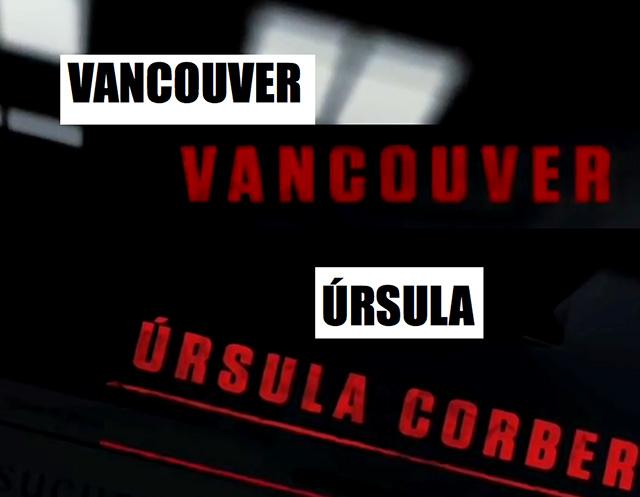
Schriftart Haus des Geldes (Netflix-Serie)
Liebe ForumsleserInnen, welche Schriftart wird im Vorspann von "Haus des Geldes" verwendet? Hier der Link zum Youtube-Video:
Das sieht auf den ersten Blick wie eine Impact mit Stempeleffekten aus ...
Edit: Auf den zweiten Blick leider nicht mehr ganz so ...
Hier sieht man es noch mal deutlicher:
Noch mal Edit: Dann wird's vielleicht die Compacta sein ...
Sieht mir nicht so aus … die Compacta ist schmäler und deren C offener.
Miſt! Dann wäre die Tungsten gemäß whatfontis ein guter Kandidat.
Und dann war da doch noch was?  Nö, hab mich getäuscht. Es gibt einiges von diesen Schriften ...
Einfach mal durchwühlen. Allerdings habe ich einige in diese Rubrik fallende Schriften da irgendwie vermisst. Gibt es da eine bessere und umfangreichere Liste und kennt jemand der hier An- und Verwesenden diese?